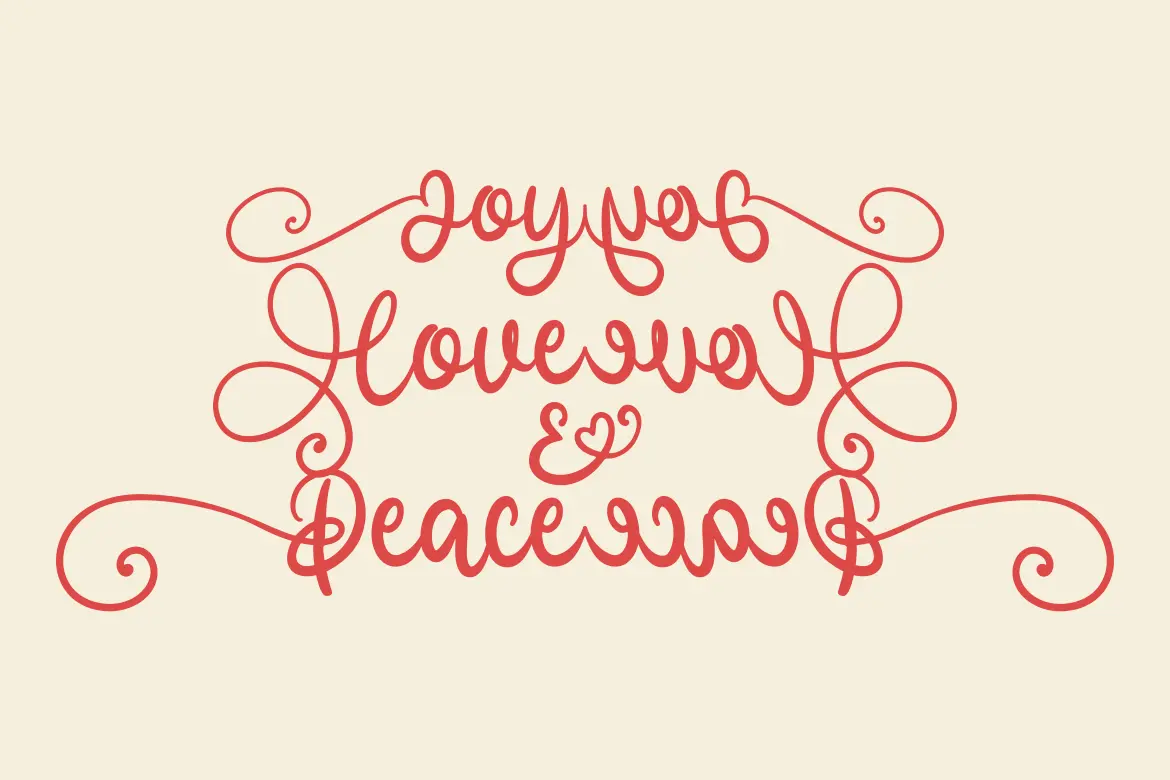
فونت دستنویس شیک و ظریف
فونت Lovely Xmas یک تایپفیس دستنویس شیک و ظریف است که برای پروژههای خلاقانه طراحی شده. این فونت با سبک منحصربهفرد خود، جلوهای رمانتیک و دلنشین به طرحهای شما میبخشد و طیف وسیعی از کاربردها را پوشش میدهد؛ از کارتهای تبریک و دعوتنامهها گرفته تا سرتیترها و طراحیهای تبلیغاتی.
⭐ ویژگیهای محصول
- فونت دستنویس ظریف و مدرن
- طراحی شیک و سبک رمانتیک
- مناسب برای کارتهای تبریک، دعوتنامهها، لوگوها و تیترها
- انعطافپذیر برای استفاده در پروژههای چاپی و دیجیتال
- افزودن حس گرما و زیبایی به هر نوع طراحی
🎯 موارد استفاده
- طراحی کارتهای تبریک کریسمس و مناسبتهای خاص
- ساخت دعوتنامههای رسمی و دوستانه
- استفاده در لوگوها و برندینگهای خلاقانه
- افزودن جلوه رمانتیک و ظریف به پروژههای گرافیکی